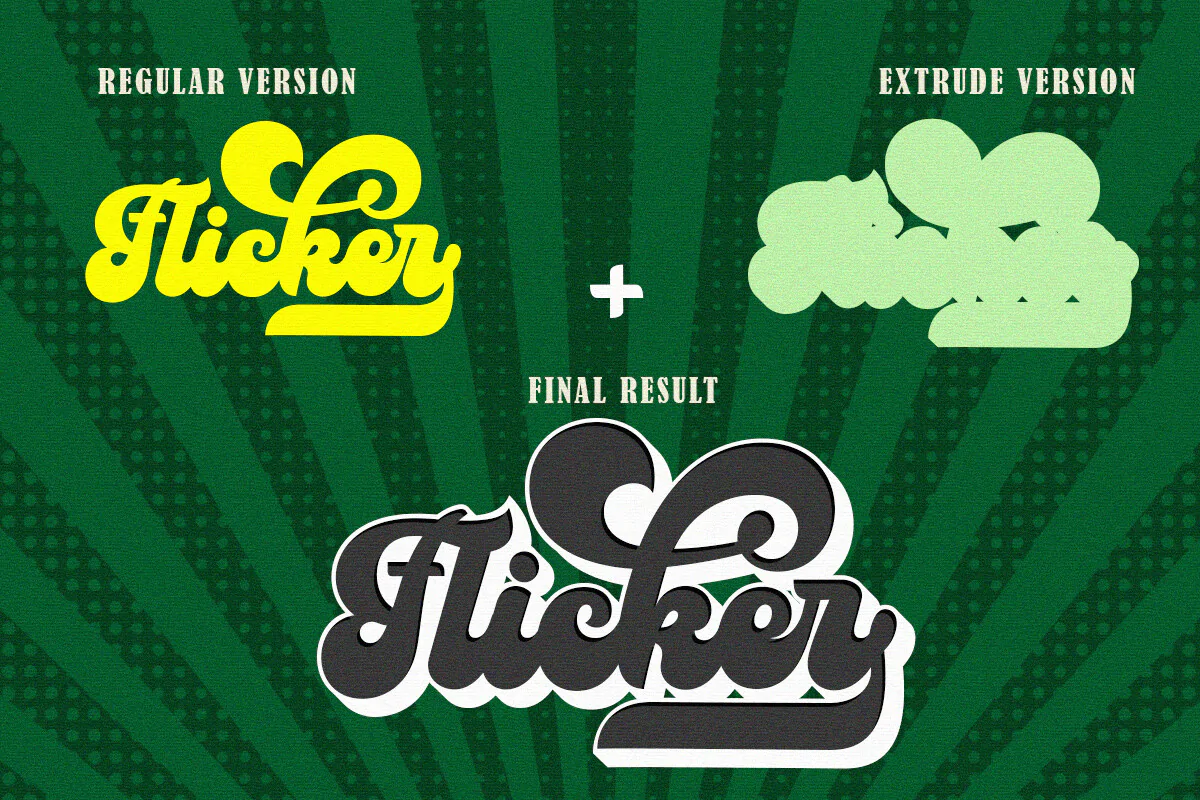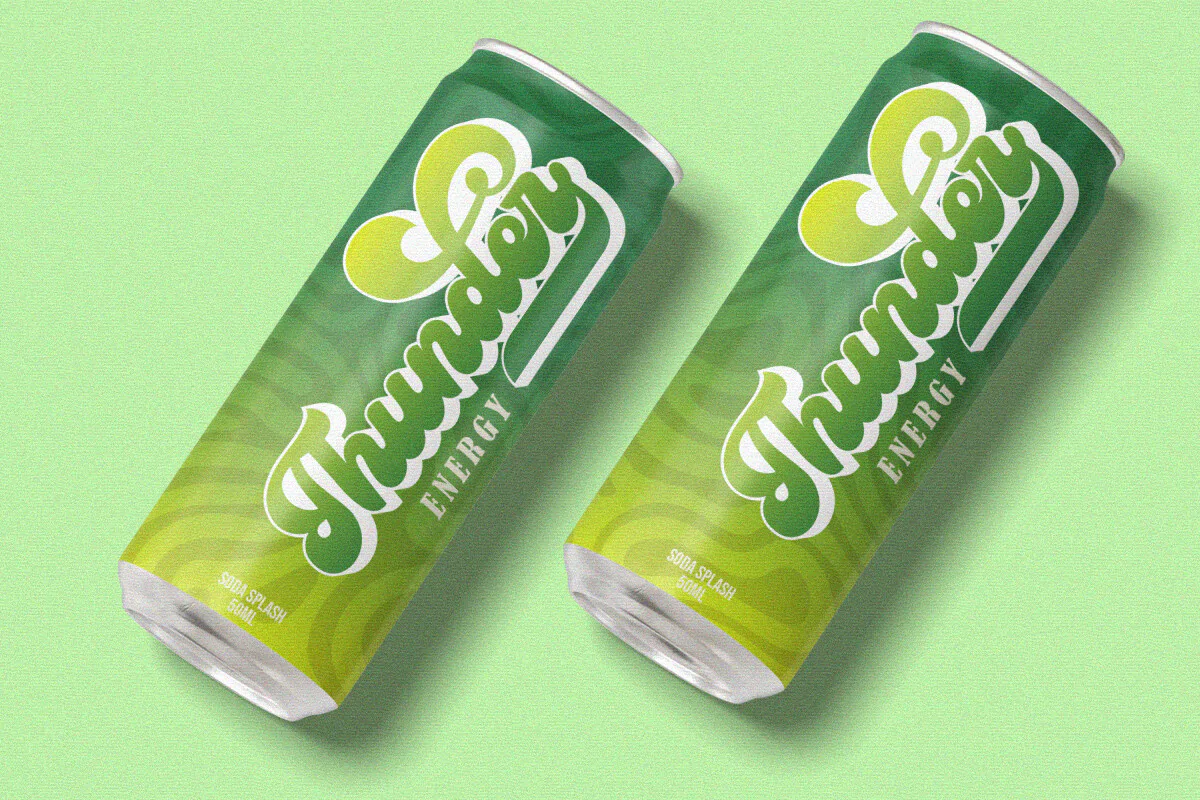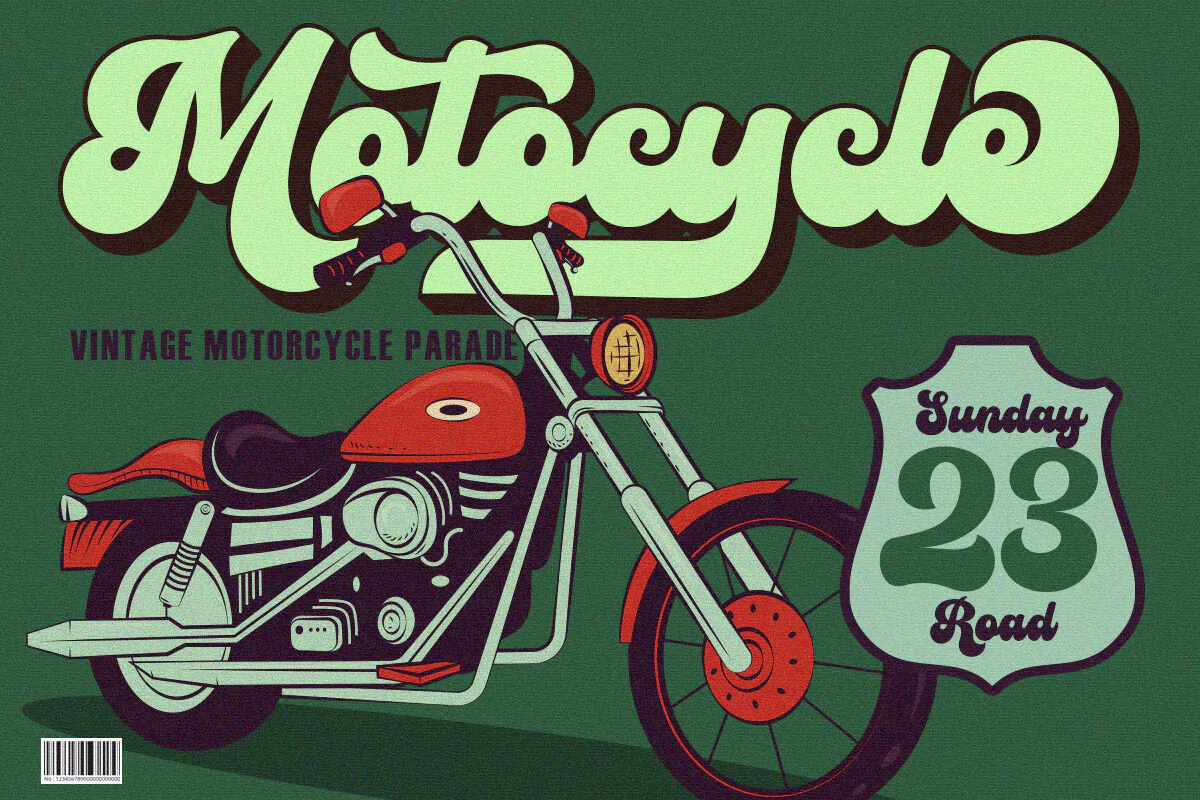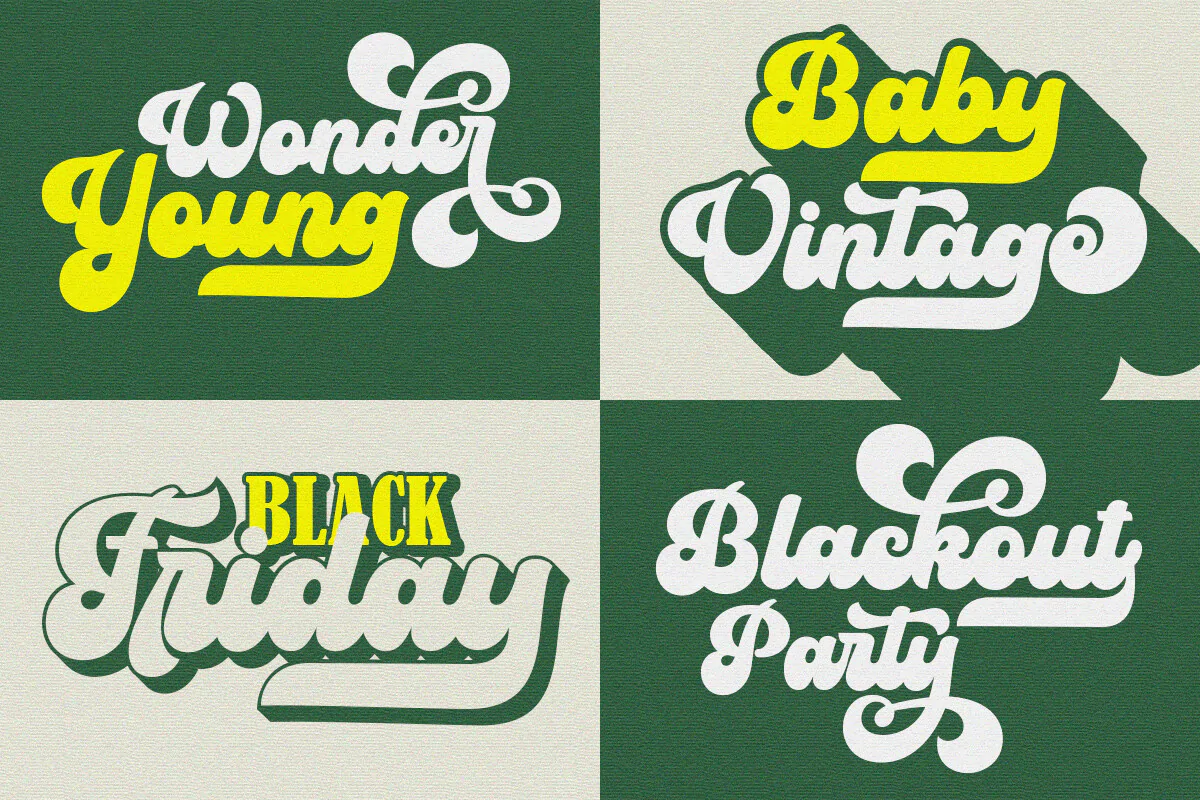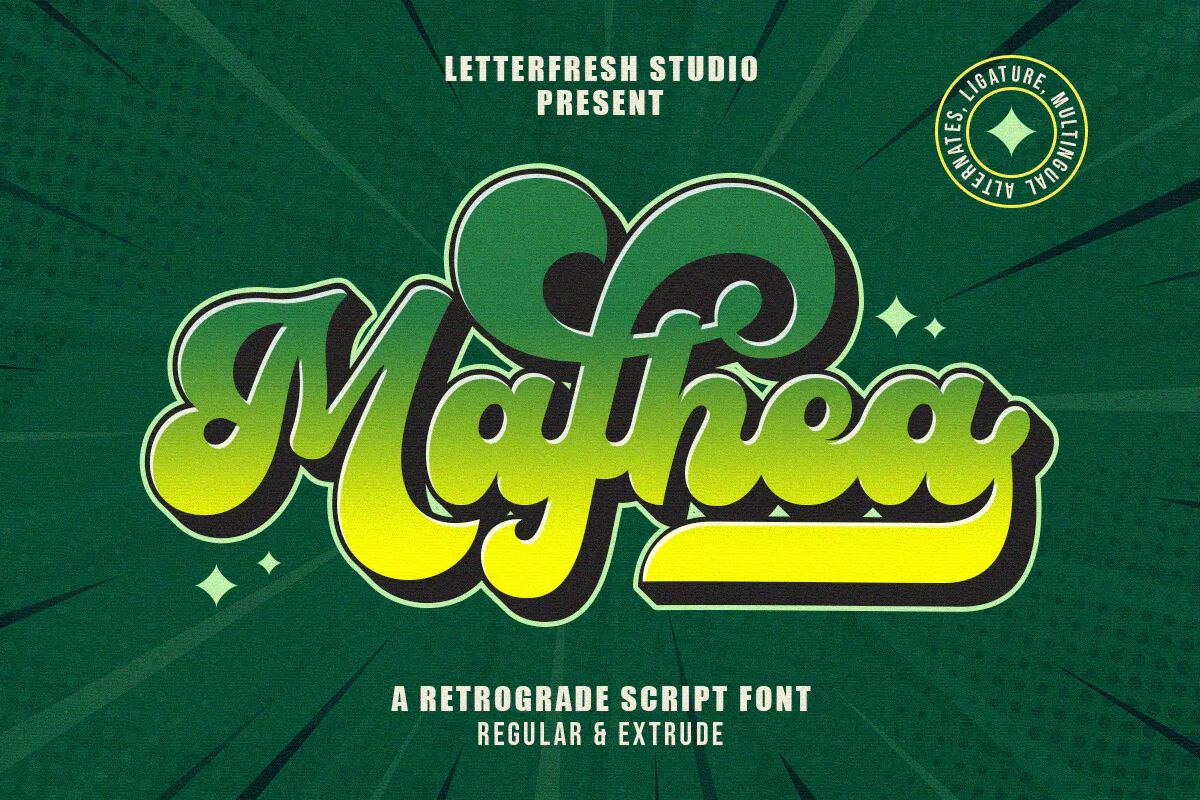
فونت رترو و وینتج Mafhea
فونت رترو و وینتج
فونت رترو و وینتج Mafhea یک قلم کلاسیک انگلیسی است که مناسب برای استفاده در طرحهای مختلف میباشد. از این فونت زیبا میتوانید در طراحی پوستر، کارت ویزیت، بسته بندی محصولات و … استفاده کنید.